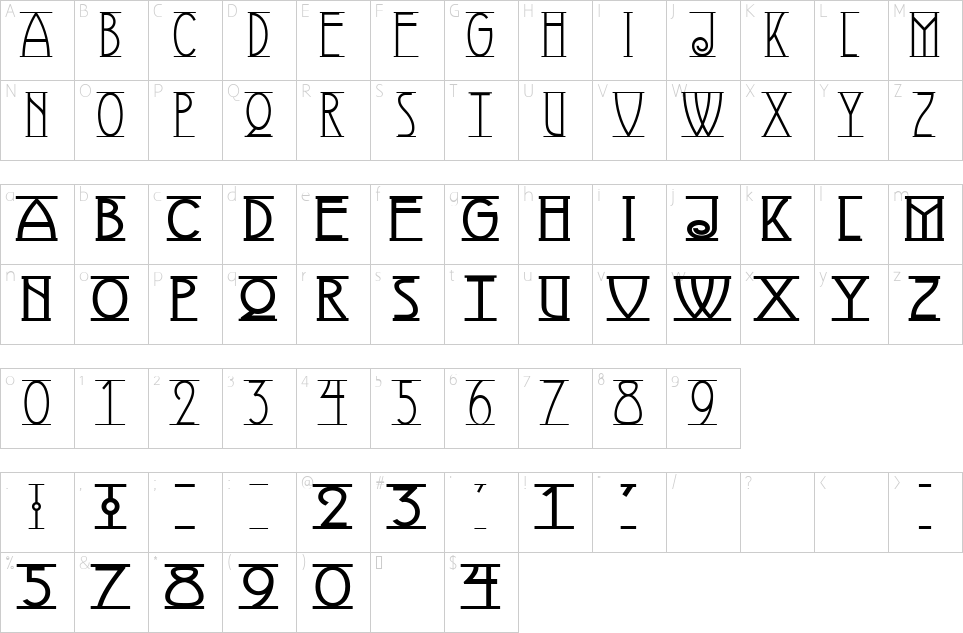
A Avignon Font é uma elegante fonte que se destaca pela sua facilidade de leitura e simplicidade. Desenvolvida por Nicks Fonts, esta fonte é perfeita para projetos que buscam um equilíbrio entre estilo e praticidade. Ideal para o design editorial, sites e pequenos logotipos, a Avignon se adequa perfeitamente a um amplo espectro de aplicações. Acesso às versões para Windows e Mac torna-a uma opção viável para um amplo espectro de usuários. Com seu design suave e moderno, a Avignon é uma fonte que não apenas enriquece a aparência de seus projetos, mas também torna o processo de criação mais fluido e envolvente. Hoje, mais de 5.590 pessoas já desfrutam do seu uso, e você pode ser a próxima em sua lista. Descarregue a Avignon Font hoje e revolucione a forma como você visualiza texto.